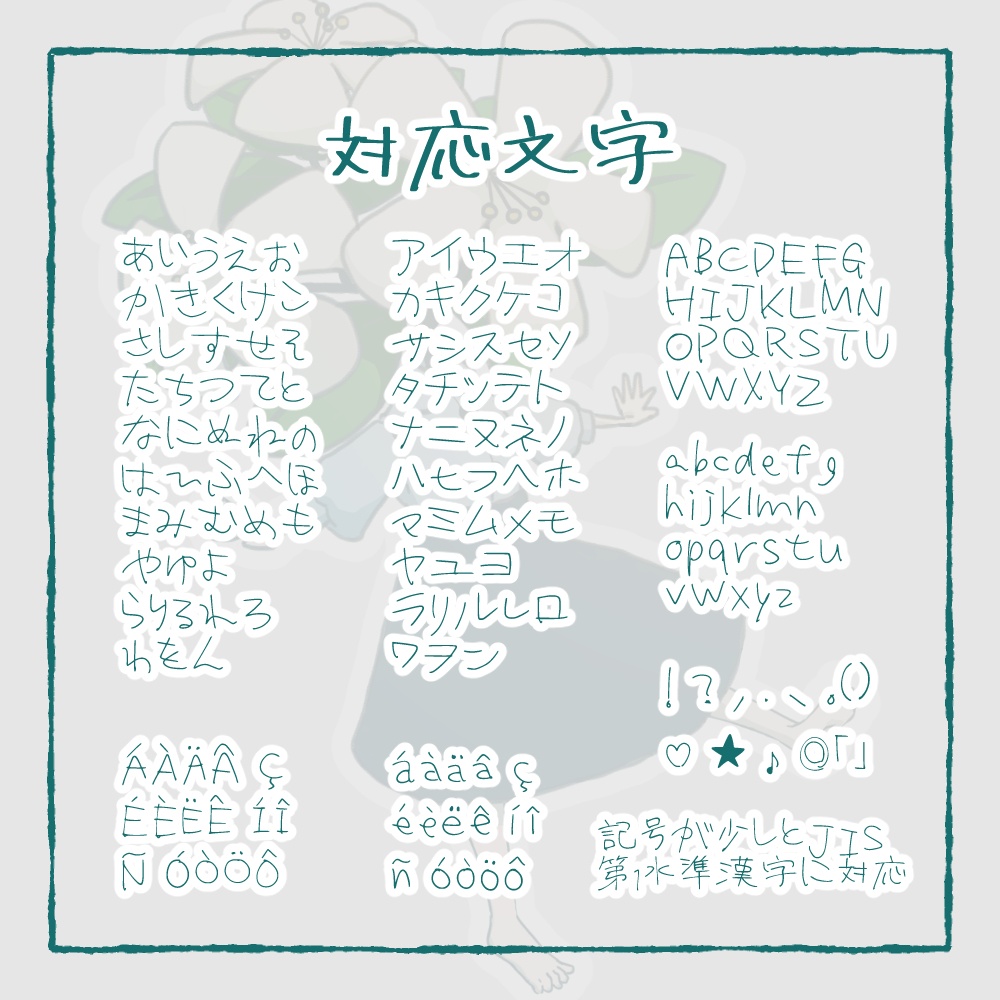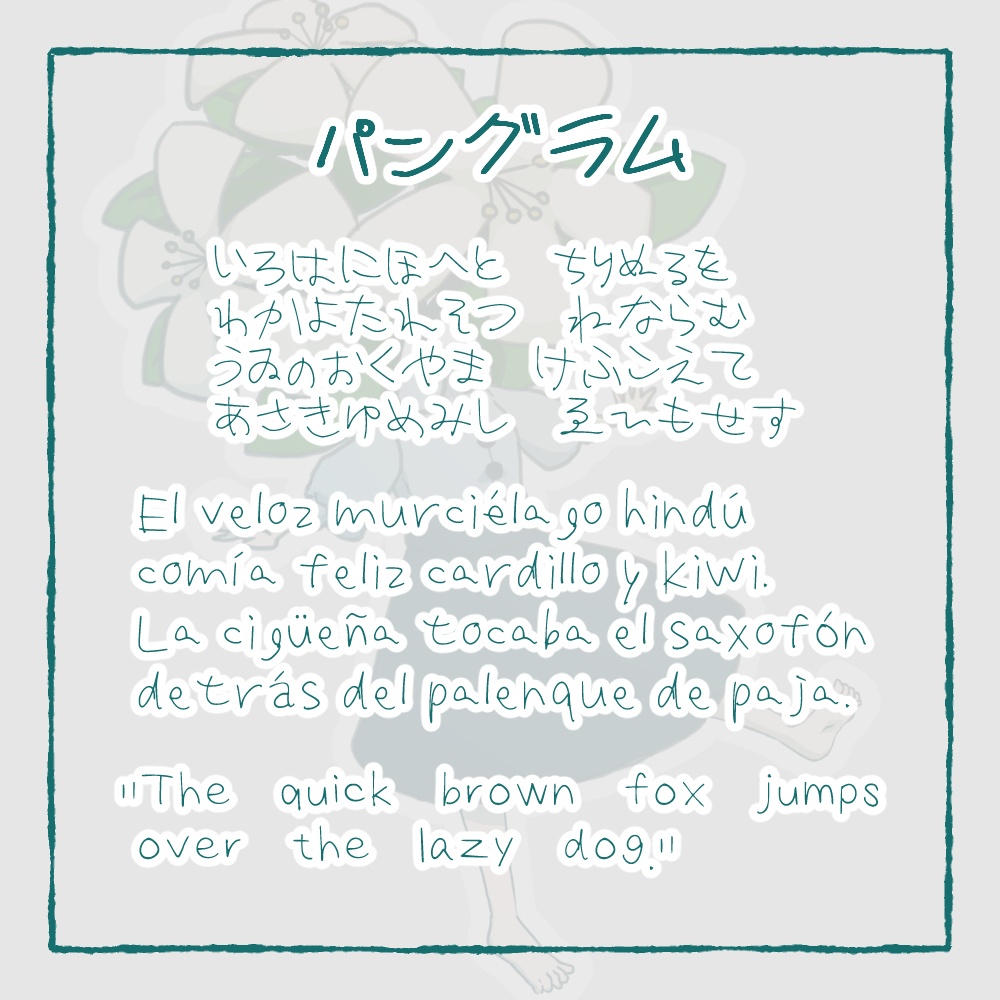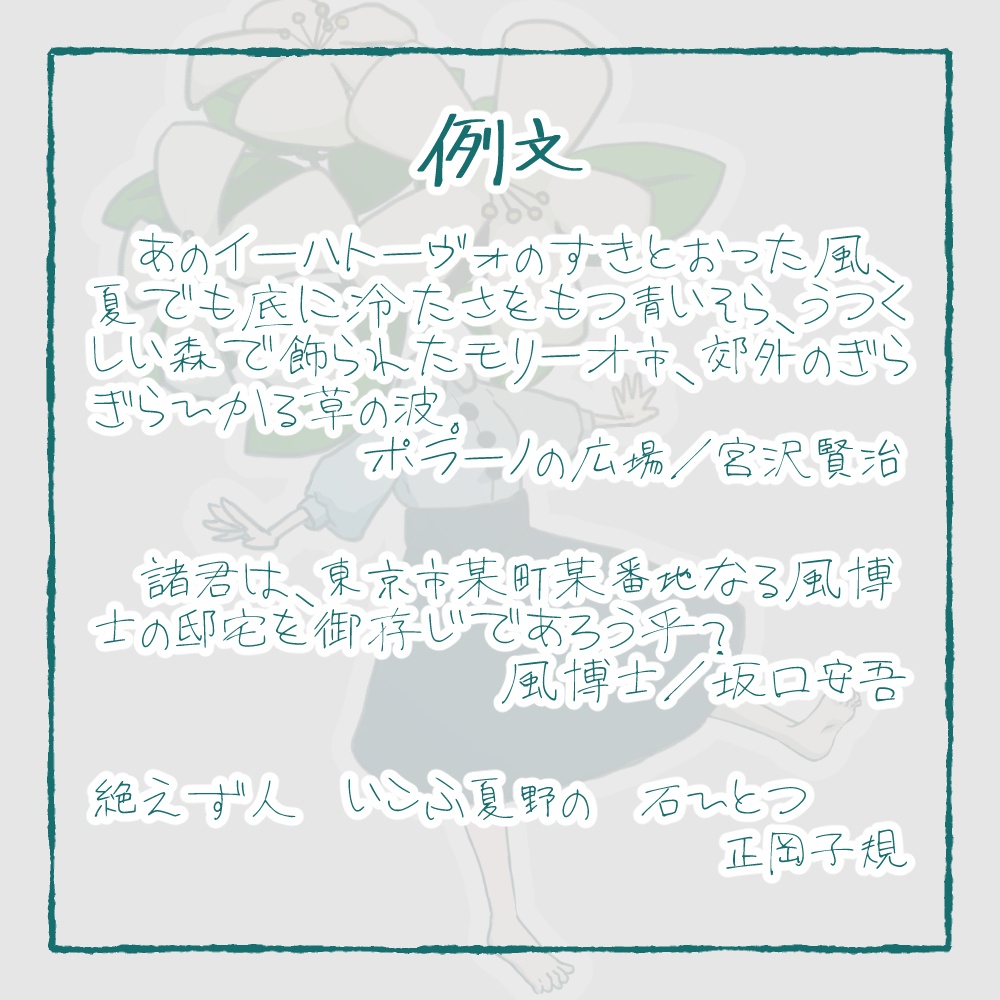
手書きのフォント「きはんのじ」です。 商用可・再配布可ですのでゲーム制作の組み込みにも使用できます。 ◾︎あるもの:ひらがな、カタカナ、アルファベット、漢字(JIS第一水準+α)、記号 対応言語:英語、スペイン語、ドイツ語 ◾︎内容物 OTF、TTF、イメージ画像、readme 無料版と投げ銭版のフォント内容は同一です。 投げ銭版にはおまけに商品イメージ画像がついています。 脱字・不備等ございましたらお手数ですがお気軽にご連絡ください。 以下の配信内で作成しました。 https://www.youtube.com/live/8U7O6vPzXTo?si=fkS4rRB8npISI-10